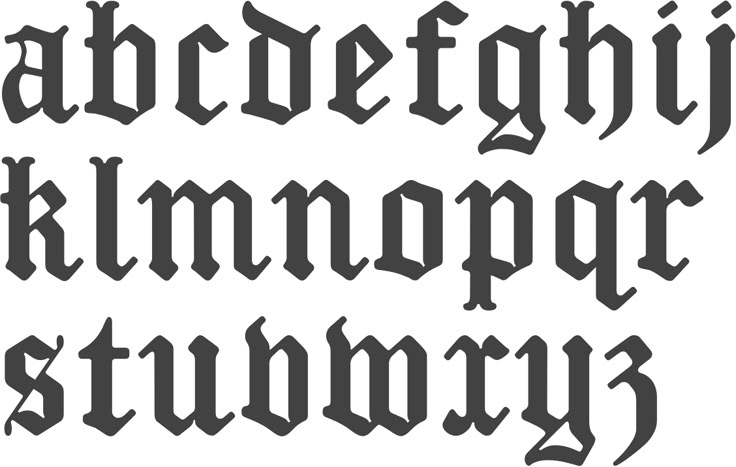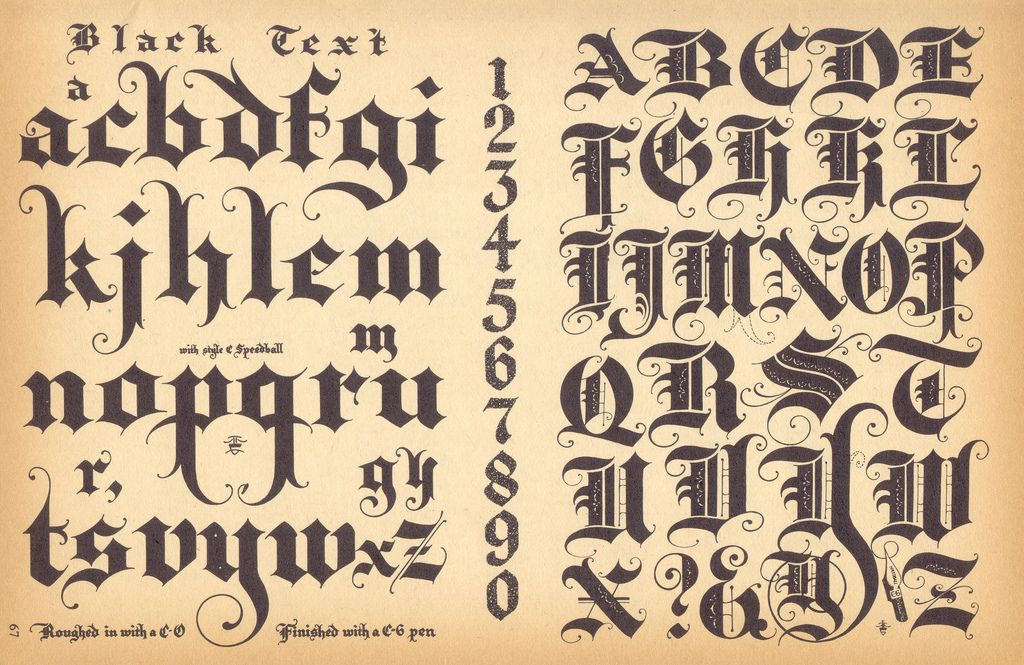
Готический шрифт. Пошаговые уроки — Часть 1. i, l, n, u, c, e
Эта статья начинает серию пошаговых уроков по готической каллиграфии. Здесь я не буду давать буквы в алфавитном порядке. Легче и быстрее начать с простых форм и переходить к более сложным. Большинство элементов разных букв повторяются, поэтому вы всегда будете отталкиваться от того, что уже знаете.
В этом уроке мы рассмотрим буквы: i, l, n, u, c, e.
Во втором уроке изучим: m, w, r, t, h, b, f, k, o, q, p, v.
В третьем уроке будут: d, g, z, x, j, y, a, s.
Четвертый урок расскажет как писать прописные буквы готического алфавита.
Можно найти много иллюстраций того, как должны выглядеть буквы готического алфавита. Ниже я приведу пример того, что мы будем изучать.
Может быть это не самый красивый пример готической каллиграфии, но он дает отличное представление об этом шрифте.
И так, приступим.